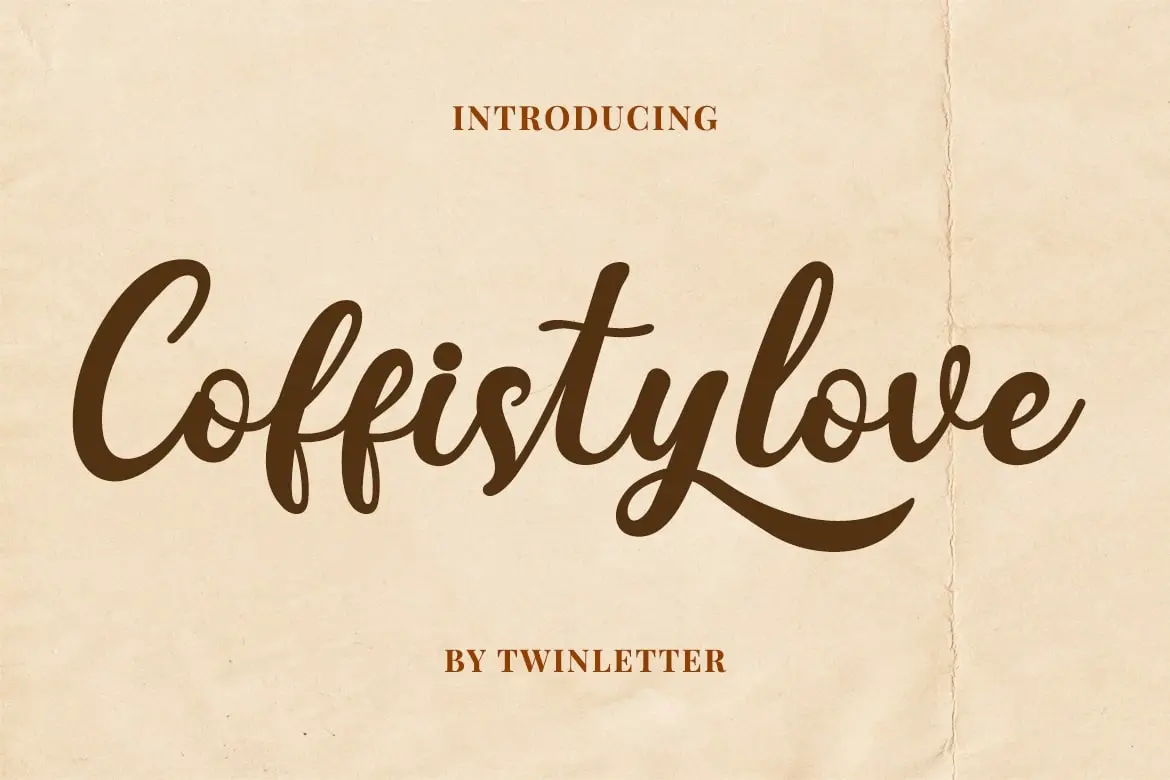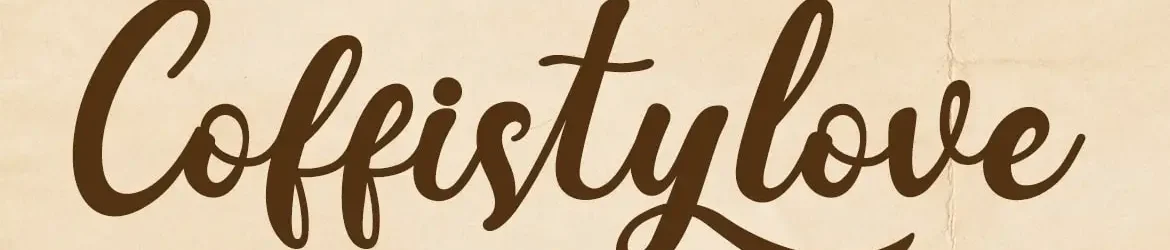
Coffistylove Font – Download Grátis
A “Coffistylove Font” é uma opção perfeita para quem busca tanto beleza quanto funcionalidade em suas projetos digitais. Desenvolvida pelo designer twinletter, essa fonte foi criada com um foco obsessivo nos detalhes, resultando num design elegante e atraente que combina prazer com sofisticação. A sua qualidade de design garante que qualquer obra feita com ela atrairá os olhares das pessoas, seja em anúncios, sites ou até mesmo no seu próprio arquivo pessoal. Ideal para aqueles que procuram uma fonte de script perfeita e única, a “Coffistylove Font” é um investimento valioso na sua coleção de recursos gráficos.